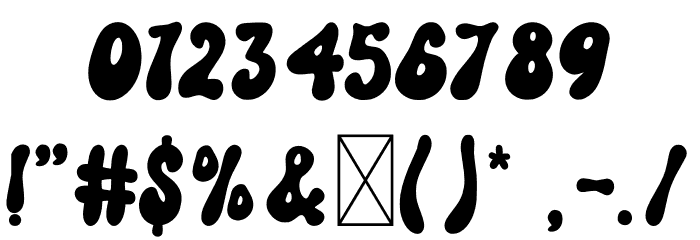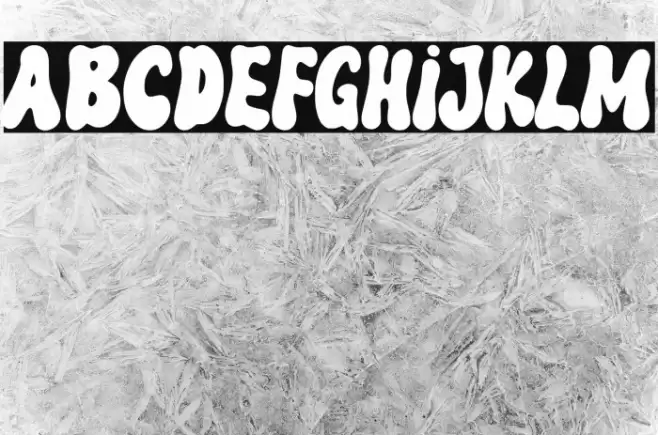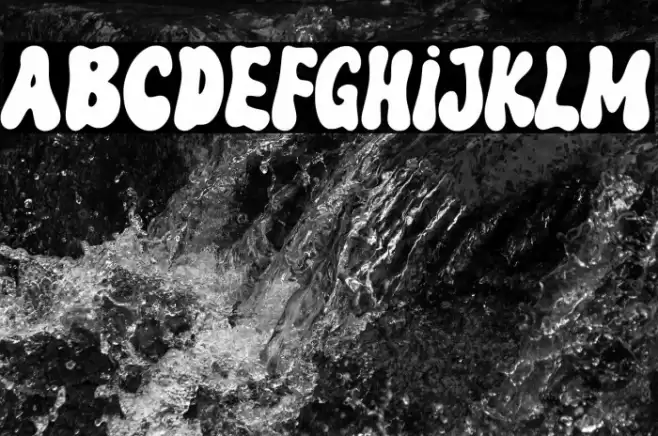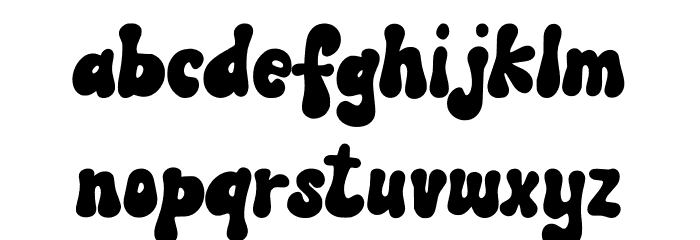
MAGICTOWNS Font
| フォントファミリー | MAGIC TOWNS |
| おすすめプロジェクト | Ideal for children's books, playful branding, party invitations, and retro-themed designs. |